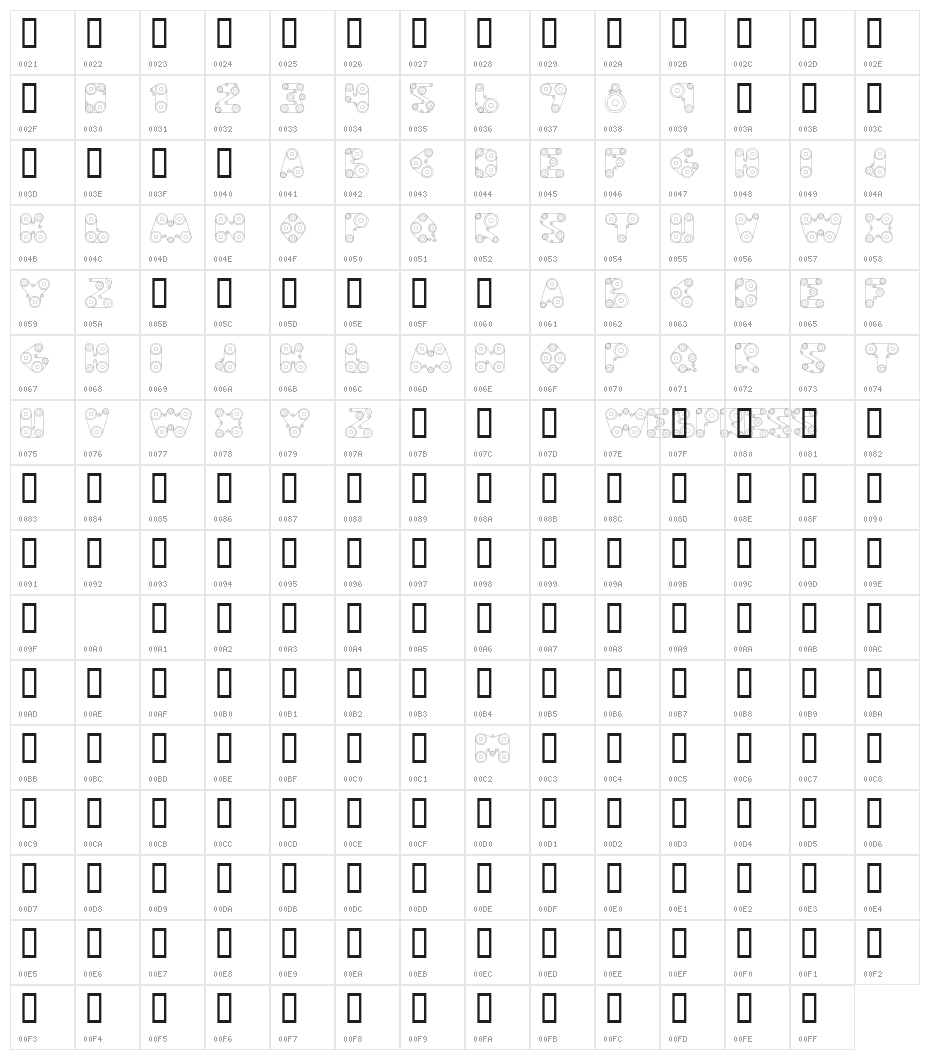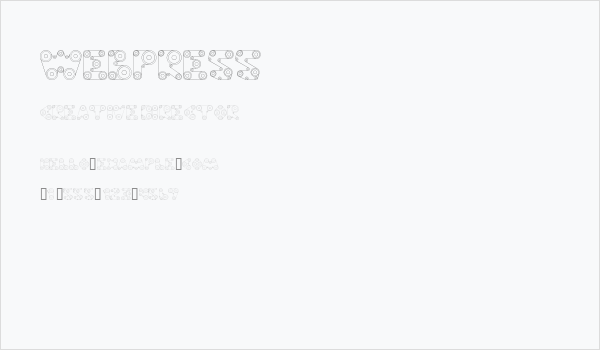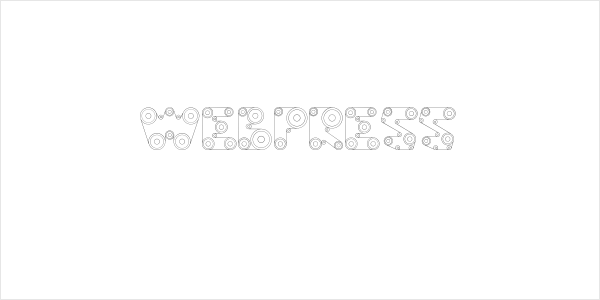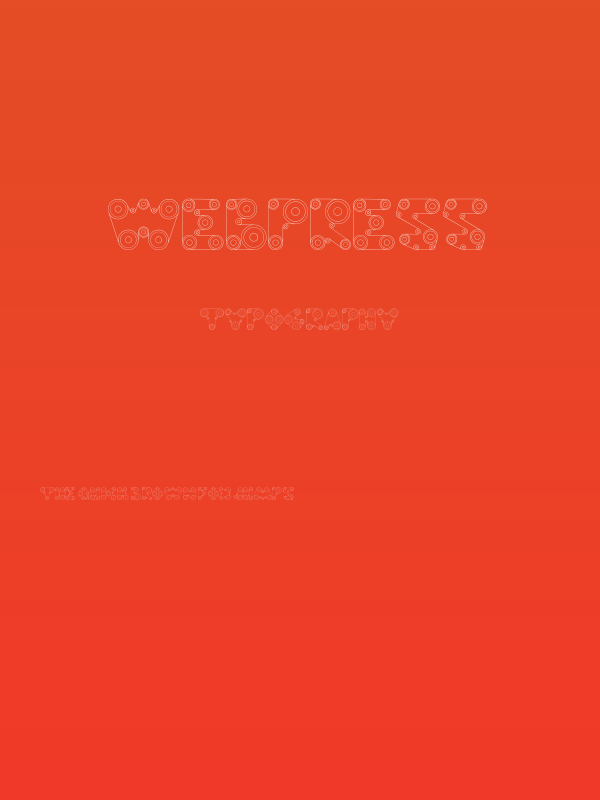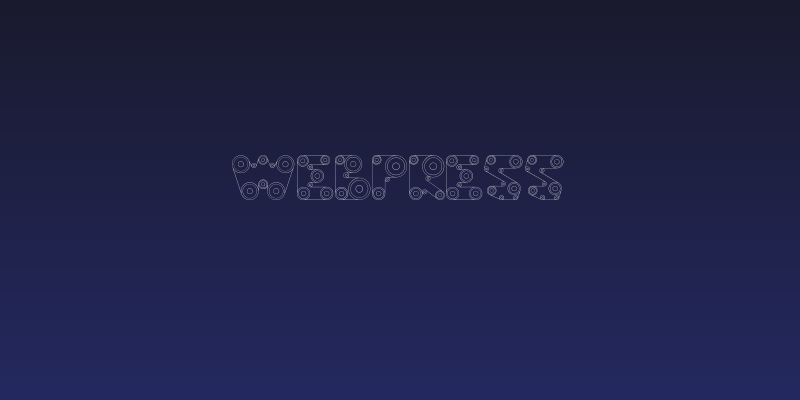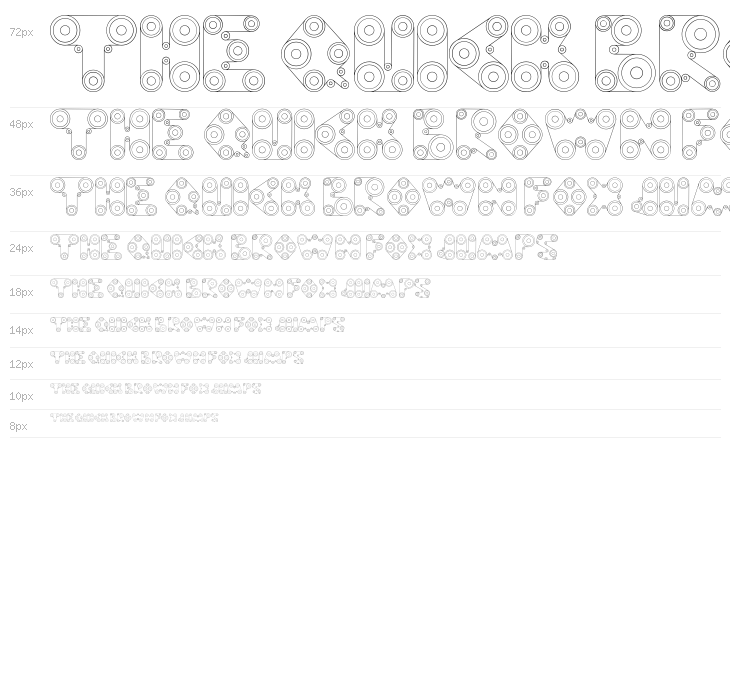
WebPress Font
| Caz de utilizare | Logos, Posters, Creative Displays |
| Proiecte propuse | Ideal for projects that require a mechanical or industrial theme, such as technology-related branding, steampunk designs, or creative posters. |